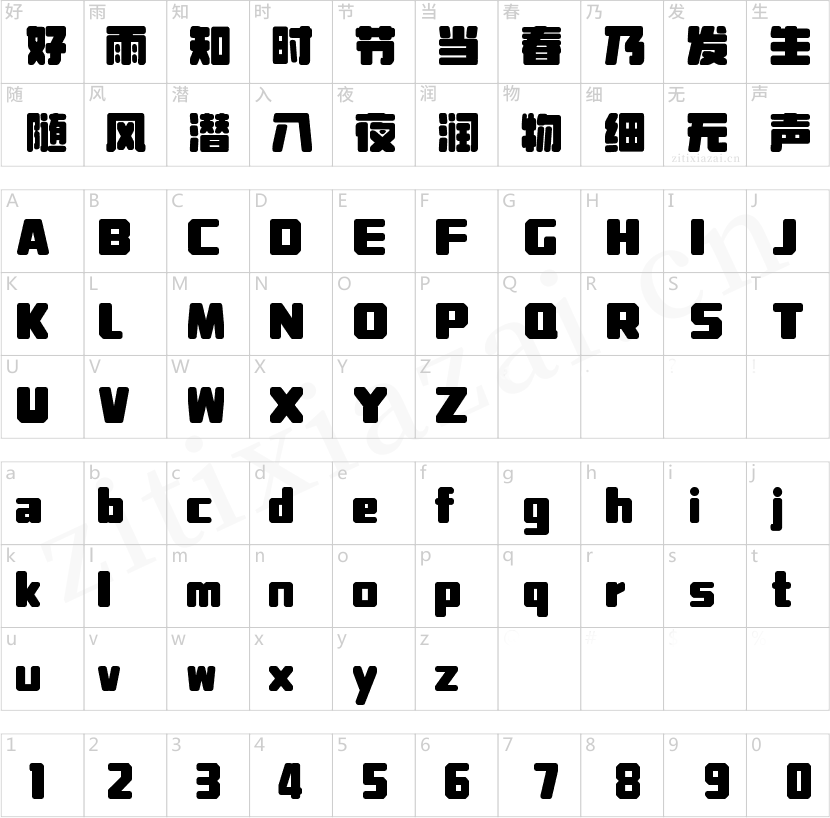
字魂福星体
字魂福星体,这款字体结构工整、笔画清晰,兼顾美观与易读性,适用于标题、正文、海报、包装、LOGO 等多种场景。字形优雅稳定,风格百搭耐看,适配日常排版与创意设计,让文字呈现更舒适、更具质感。字魂福星体一笔一画,皆是细节,以均衡的比例、流畅的线条打造舒适视觉体验,字形端正大气,风格简约现代。无论是商业设计、品牌宣传还是日常排版,都能轻松驾驭,让文字更有格调与力量。字魂福星体字体下载。
字魂字体字魂福星体字体是由字魂创意字库设计并生产的一款可商用的字体,被收录于字魂先锋系列。该字体支持GB-2312标准,包含6942个中文、字母、符号和数字,字体类型偏向黑体,具有可爱、圆润的风格,在市面上广泛用于包装印刷、印刷品&包装、媒体&H5等场景。